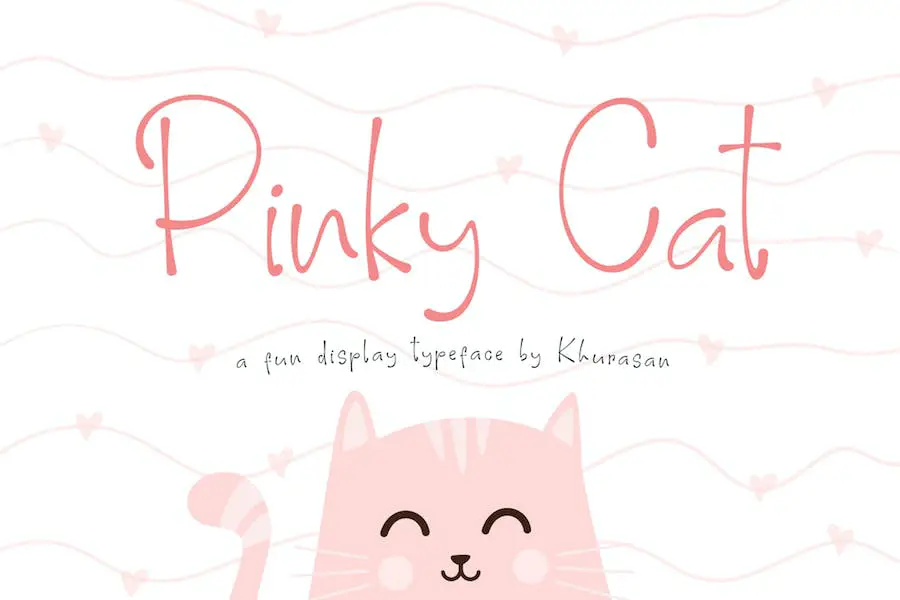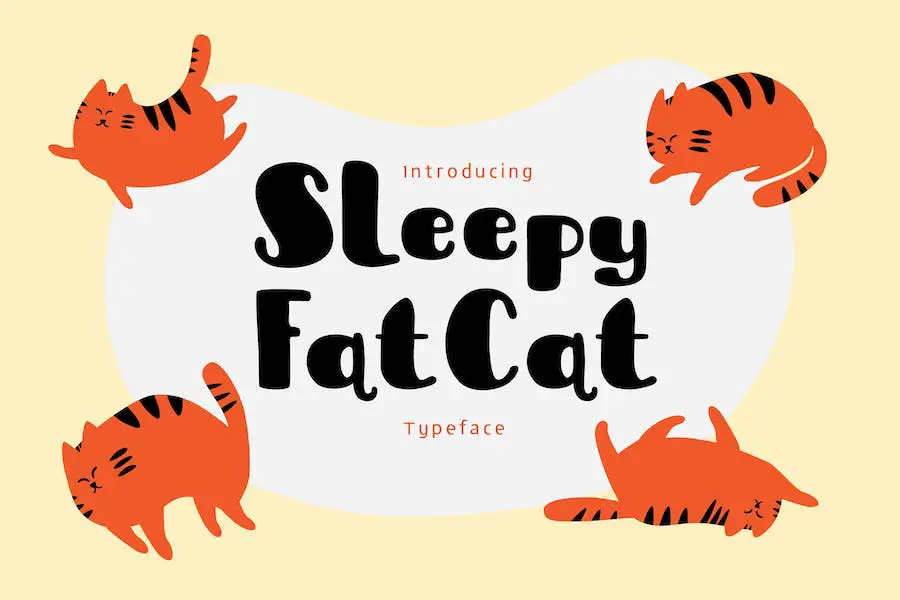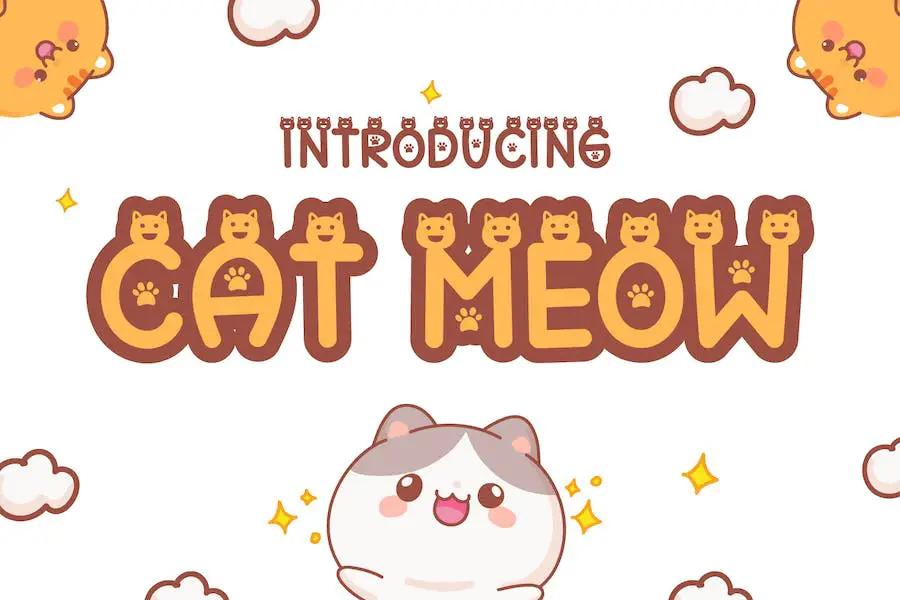
22 лучших кошачьих шрифта 2023 года (бесплатно и премиум)
Опубликовано: 2023-07-18Вы графический дизайнер и ищете идеальный шрифт для ваших проектов? Не смотрите дальше! В этом посте мы рассмотрим 22 лучших кошачьих шрифта, которые гарантированно добавят кошачьего очарования вашим проектам.
Но подождите, вам может быть интересно: «Почему кошачьи шрифты?» Что ж, позвольте мне сказать вам, что эти шрифты не только визуально привлекательны, но они также обладают способностью вызывать чувство игривости и изящества, которые могут действительно улучшить эстетику вашего дизайна.
Теперь давайте углубимся в то, что эта статья приготовила для вас. Мы тщательно составили список из 22 лучших кошачьих шрифтов, доступных сегодня на рынке. От причудливых отпечатков лап до элегантных силуэтов — каждый шрифт в этой коллекции придает столу свой неповторимый шарм.
И если вас интересует популярность этих шрифтов, позвольте мне поделиться с вами некоторыми статистическими данными. Согласно недавнему опросу, количество дизайнов с кошачьей тематикой растет, и спрос на них вырос на 35% со стороны клиентов, которые хотят включить этих очаровательных существ в свой бренд.
Итак, если вы хотите оставаться на шаг впереди и впечатлять своих клиентов своим выбором дизайна, эти шрифты для кошек — то, что вам нужно.
Теперь давайте взглянем на то, что вы можете ожидать от этой статьи. Мы изучим функции и характеристики каждого шрифта, предоставив вам информацию о его удобстве использования и совместимости с различным программным обеспечением для дизайна.
Кроме того, мы поделимся советами и рекомендациями о том, как эффективно использовать эти шрифты для улучшения ваших дизайнерских проектов. Итак, работаете ли вы над логотипом, плакатом или веб-сайтом, эти кошачьи шрифты добавят дополнительный шарм и креативность, которые выделят ваш дизайн из толпы.
Приготовьтесь исследовать мир кошачьих шрифтов и найти идеальный вариант для вашего следующего проекта!
Лучшие премиальные кошачьи шрифты
Хотите вывести свои дизайнерские проекты на новый уровень? Наша коллекция шрифтов премиум-класса обязательно впечатлит. Взгляните на эти первоклассные варианты и найдите идеальный шрифт, который украсит ваш дизайн. Не пропустите — идите вперед и исследуйте лучшие доступные кошачьи шрифты!
Кот
The Cat — это фантастический кошачий шрифт, который добавляет веселья и привлекательности любому дизайн-проекту. Благодаря своему каллиграфическому стилю он идеально подходит для создания красивых приглашений, поздравительных открыток, материалов для брендинга, визитных карточек, цитат, плакатов и многого другого!
Этот милый кошачий шрифт выделит ваш дизайн и привлечет внимание. Создаете ли вы причудливое приглашение на день рождения или игривое графическое изображение цитаты, шрифт The Cat добавит дополнительную дозу очарования.
С помощью шрифта The Cat вы можете создавать привлекательные плакаты, которые заставят людей остановиться и обратить на них внимание. Его игривый и увлекательный стиль привлечет людей и заставит их хотеть продолжить изучение вашего дизайна.
Суши Кэт
Sushi Cat — это очаровательный и игривый дисплейный шрифт, который привнесет нотку причудливости в ваши дизайнерские проекты. Этот симпатичный кошачий шрифт с очаровательными каракулями «Sushi-Cats» идеально подходит для добавления веселого и беззаботного элемента в ваши творческие начинания.
Уникальные и привлекательные каракули, представленные в Sushi Cat, мгновенно привлекут внимание вашей аудитории. Создаете ли вы поздравительную открытку, плакат или веб-сайт, этот шрифт поможет вам создать запоминающуюся и визуально привлекательную часть.
Красота Sushi Cat заключается в его способности привнести в ваши проекты ощущение игривости. Рисунки очаровательных котиков-суши придают причудливую и приятную атмосферу любому проекту.
Йелло Кэт
Yello Cat — это симпатичный кошачий шрифт, который добавит очаровательный штрих в любой проект графического дизайна. Благодаря своему игривому и дружелюбному внешнему виду этот шрифт идеально подходит для создания дизайнов, требующих нотку привлекательности.
Его уникальный стиль и милые глифы на тему кошек делают его выдающимся выбором для дизайнеров, которые хотят включить в свою работу забавный и причудливый элемент.
Создаете ли вы плакат, логотип или графику для социальных сетей, Yello Cat обязательно вызовет улыбку на лицах вашей аудитории. Попробуйте и дайте волю своему творчеству!
Кошка Мяу
Cat Meow — это удивительный и симпатичный дисплейный шрифт с великолепными изображениями кошек. Это идеальный выбор для поделок на кошачью тематику. Благодаря своему очаровательному дизайну он добавит игривости любому дизайн-проекту.
Отличительной особенностью Cat Meow является коллекция очаровательных клипартов Cat. Эти замысловатые иллюстрации добавят вашему дизайну дополнительный уровень привлекательности.
Если вы хотите создать причудливую поздравительную открытку или добавить изюминку в постер, эти клипарты с кошками сделают ваш дизайн выделяющимся из толпы.
Помните, мир дизайна постоянно развивается и полон бесконечных возможностей. Так что продолжайте экспериментировать, продолжайте творить и продолжайте расширять границы своего воображения.